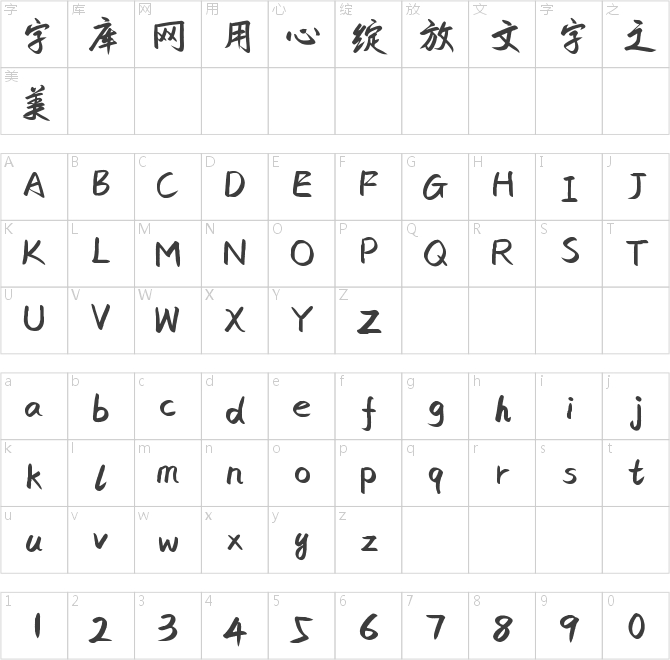
字魂252号-凤仪手书
字魂252号-凤仪手书是一款手写字,字体的行笔自然,形神兼备、气贯笔端。部分笔画之间留下了相互牵连,字体显得迅捷流畅,适用于宣传设计、商业广告和产品包装设计。
字魂252号-凤仪手书字体zihun252hao-fengyishoushu字库是一款让人赏心悦目、百看不厌的中文字体,适合各类广告和产品包装设计应用,字体大小16.94MB,格式为ttf字体,上传用户是晓语无声,作者/版权方为字魂